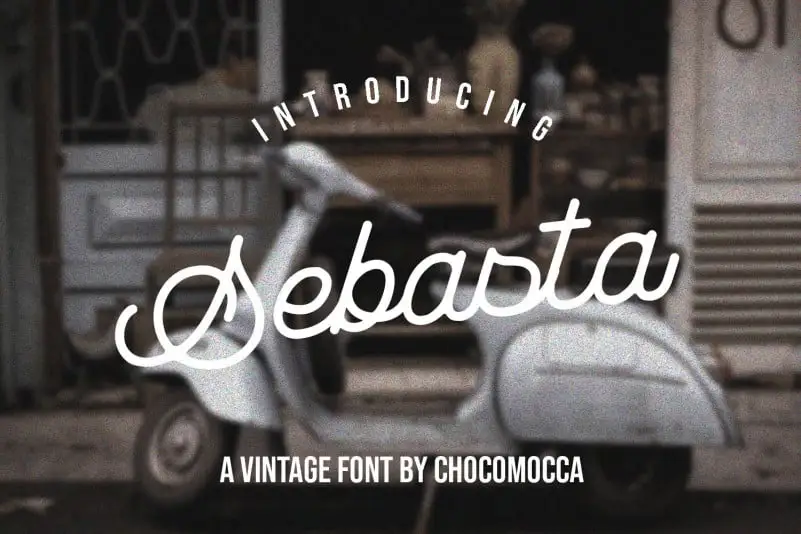
Sebasta Vintage Font – Download Grátis
A Sebasta Vintage Font é uma tipografia script monolinea altamente versátil. Permite ao designer dar personalidade a cada palavra de um projeto através do poder de escolher entre uma variedade de caracteres, criando design de tipo incrível e estiloso. Ela foi criada e compartilhada pelo Choho Mocha, mantendo todos seus defeitos naturais e elegantes que tornam-a perfeita para designs vintage. Ideal tanto para artesanato moderno como envelope lettering, design de livros, cartazes ou qualquer projeto de branding, ela traz um toque de design retro e vintage aos seus trabalhos. A Sebasta Vintage Font é uma ótima escolha para aqueles buscando adicionar um ar despojado e charmoso a suas criações gráficas.